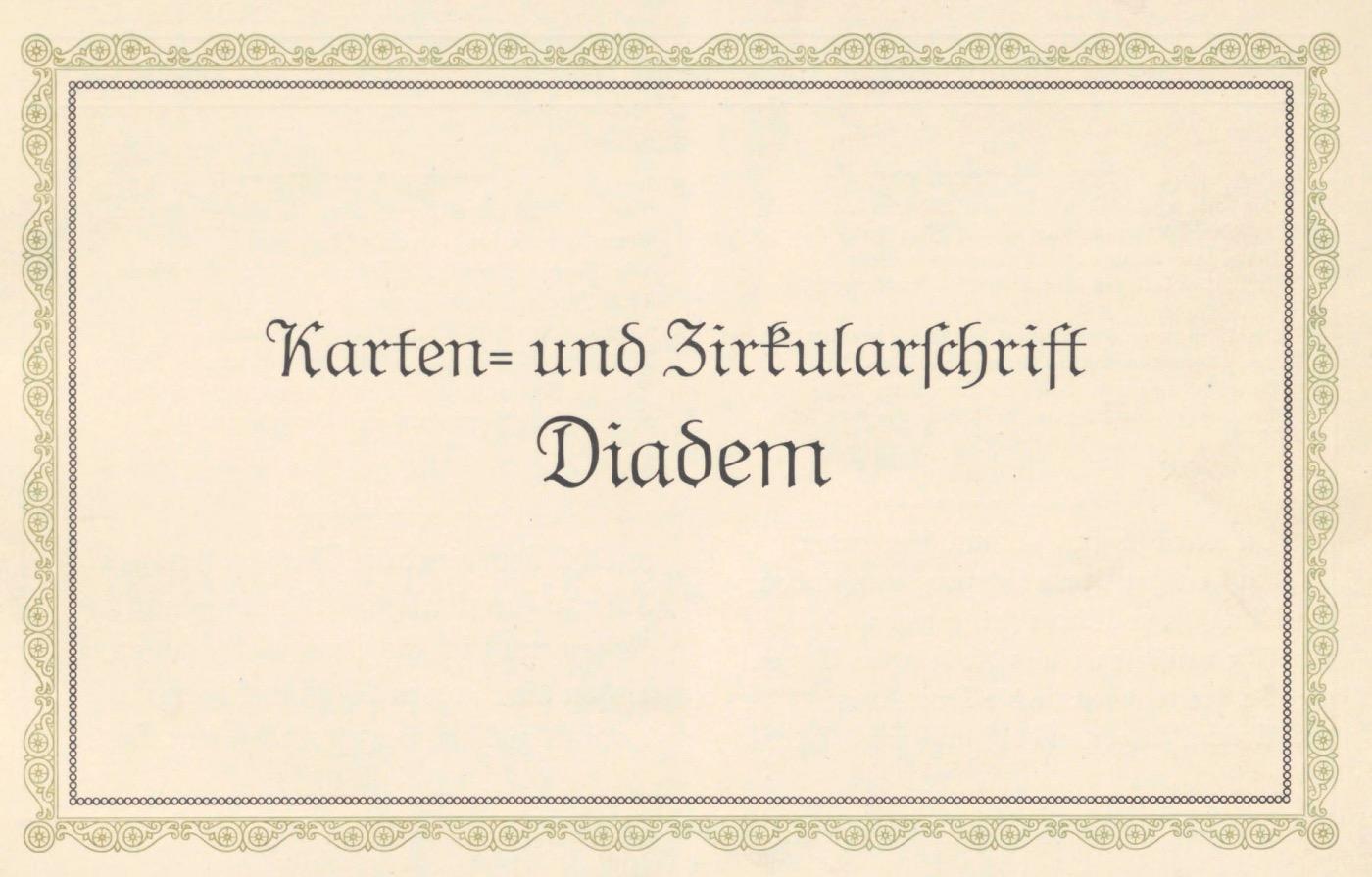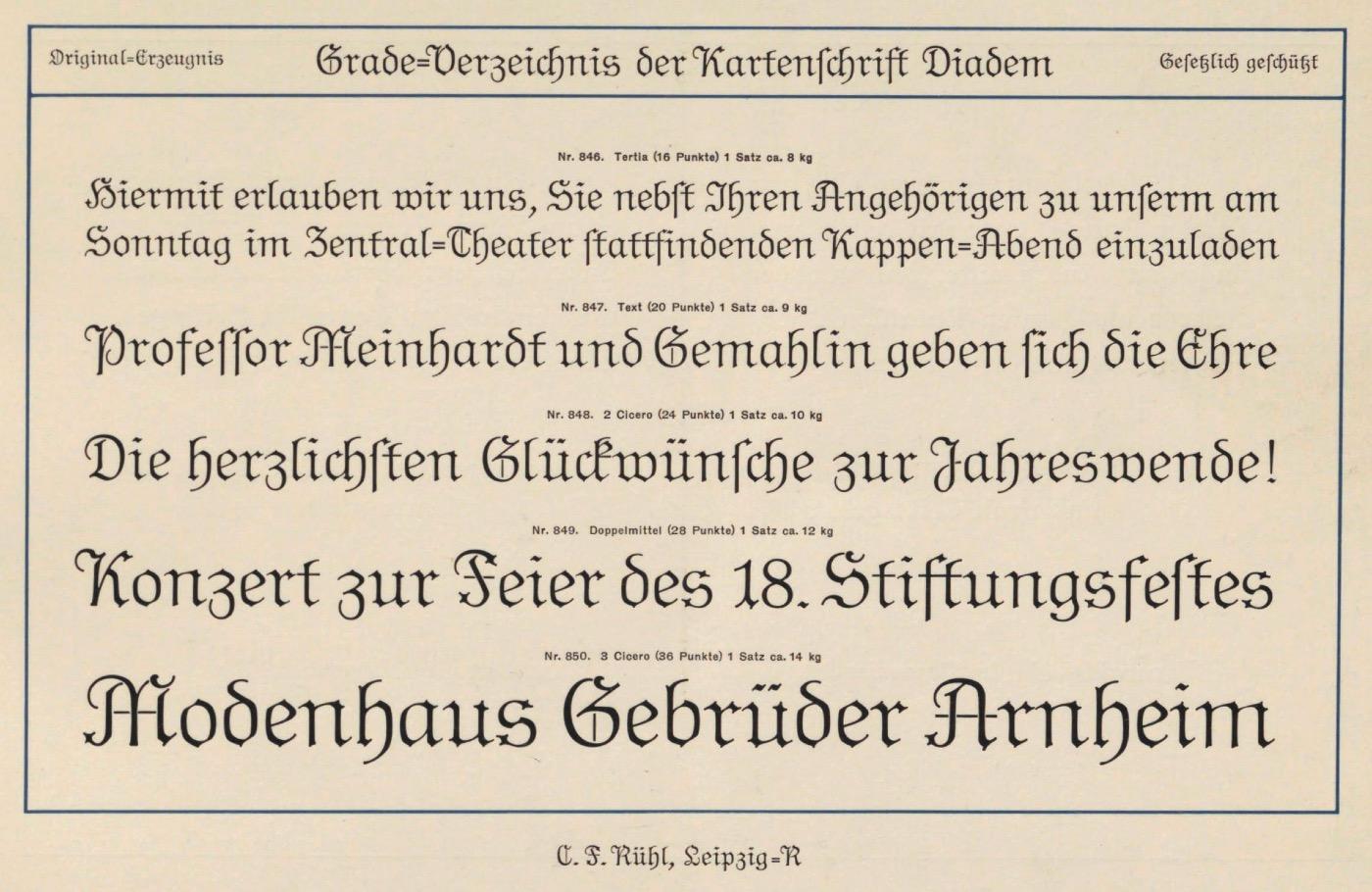
Font-Wiki: Kartenschrift Diadem
• 1912
• Antiqua dekorativ
Die Kartenschrift Diadem erschien 1912 bei der Leipziger Gießerei C.F. Rühl. Die Schrift von Georg Schiller verbindet Elemente von gebrochenen Schriften und Antiqua-Schriften in einem Entwurf.